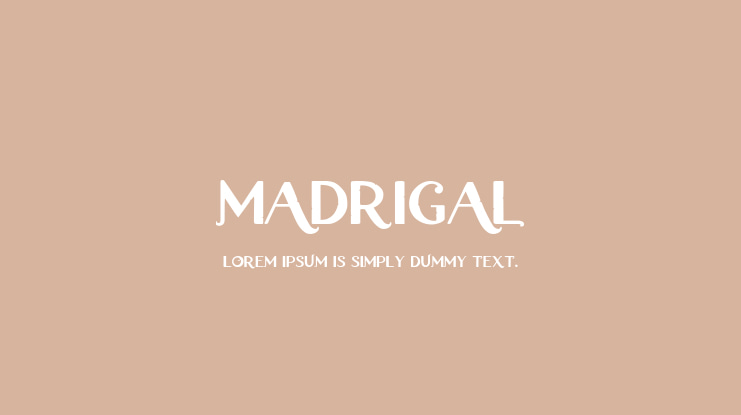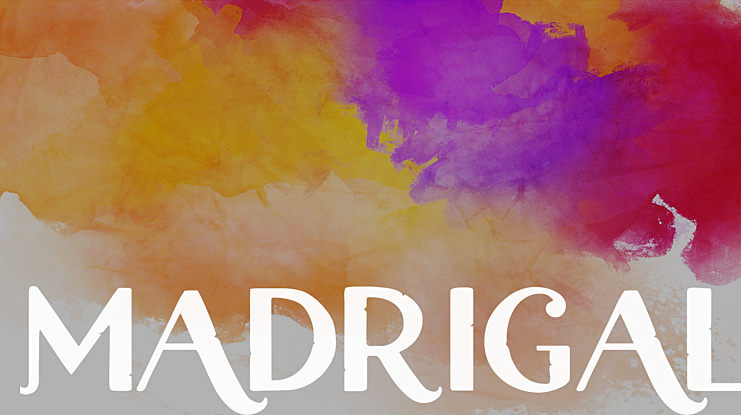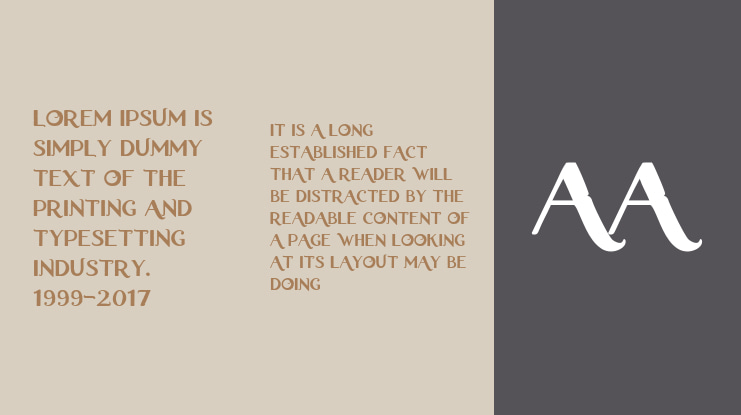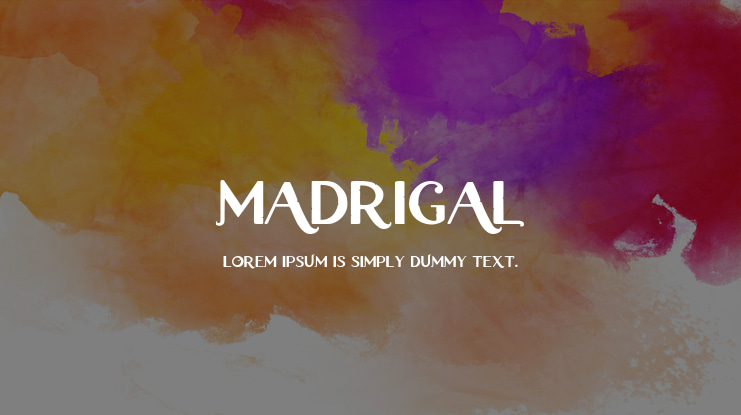
Madrigal Font
La fuente está basada en su logotipo, la fuente fue recreada por NubeFonts a partir del alfabeto que se compro en la página ETSY gracias a que teníamos dinero en PayPal